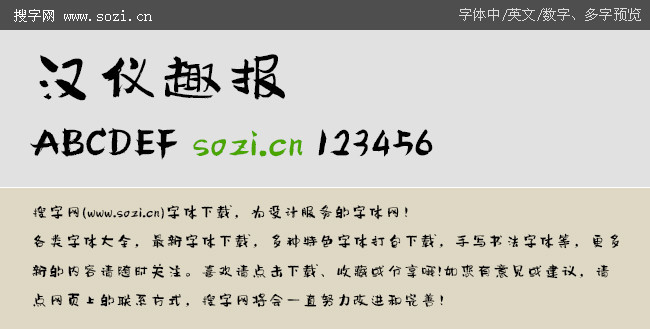
漢儀趣報
搜字網(wǎng)給大家提供一款漢儀趣報中文字體下載,漢儀趣報體是一款極具創(chuàng)意的全新字體,該字體筆畫較粗,類似于筆刷構(gòu)成,簡短的字體結(jié)構(gòu)看起來簡單干凈,適合應(yīng)用于藝術(shù)設(shè)計(jì)、平面宣傳設(shè)計(jì)、網(wǎng)頁設(shè)計(jì)、海報設(shè)計(jì)等等應(yīng)用。(本字體為個人非商用版,如需要商用請聯(lián)系漢儀公司購買版權(quán))